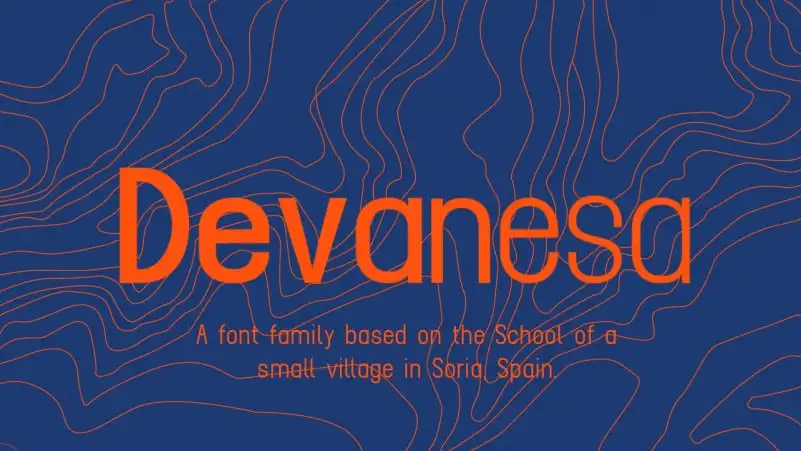
A Devanesa Free Font é uma elegante e minimalista fonte sans-serif vintage, com contornos arredondados inspirada em traços a mão e impressão antigas. Seu design limpo e bem estruturado evoca a delicadeza de letras artesanalmente desenhadas, oferecendo um toque de nostalgia aos designs contemporâneos. Ideal para quem busca uma solução minimalista, essa fonte vem completa com números e símbolos além da alfabeto em maiúsculas, tornando-a perfeita para a criação de qualquer tipo de design gráfico — seja ele web, impressão ou publicidade digital.